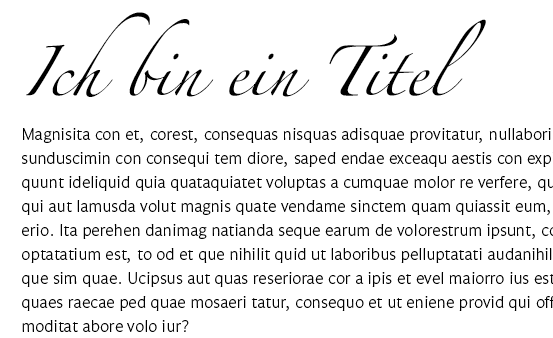
Serifenlose für Dipl-Arbeit, zur Zapfino
meine Freundin schreibt gerade ihr schriftliches Diplom in der Innenarchitektur, Thema "Flagshipstores".
Für Titel, besondere Hervorhebungen und u.U. Überschriften will sie unbedingt eine Zapfino. Und für den Fließtext eine Serifenlose. Bei beidem lässt sie nicht mit sich reden, auch Trennungsdrohungen helfen nicht. Immerhin hat sie sich von der Verdana abbringen lassen, was ich mir selbst hoch anrechne!
Nunja, und bei der Fließtextschrift schwimme ich gerade noch etwas. Hier haben eben viele Anforderungen/Eigenschaften Einfluss, ungefähr geordnet nach Wichtigkeit:
- angenehme Lesbarkeit auch bei 40+ Seiten
- passend zur Zapfino
- Überdrehtkeit/"Over-Dressed-heit" des Modebusiness
- Technische Anmutung bzw Konstruiertheit von Grundriss-Auszeichnungs-Schriften
- Verdana-Ähnlichkeit
Na, Ideen?
FF Fago? Frutiger? Univers? Museo Sans? Akzidenz-Grotesk? Neo Sans? Myriad? News Gothic? Avenir? DeLargo? Interstate (Light)?
PS: Habe persönliche Ressentiments gegen eingeschossige "a".
PPS: Gotham ist mir zu 'hip'.
Deine (OK, ihre) Kriterien klingen für mich erstmal relativ äh, schwer zu vereinen (gute Lesbarkeit, aber so technisch wie ne Grundrisszeichnung? Ich denke, da muss ne Priorisierung her. Klingt ein bisschen nach eierlegender Wollmilchsau :-) ).
For what it's worth und ganz spontan: Die angenehmst zu lesende Serifenlose, die mir auf Anhieb einfällt, ist die :biglove:Legato von Evert Bloemsma. Was da in den Balkenstärken ganz fein passiert, könnte man, wenn mans nicht besser weiß, auch für einen feinen kalligraphischen Duktus halten (tun wirklich manche Laien) – könnte also evtl einigermaßen zur Zapfino passen?
30-Sekunden-Schnelltest anbei (das ist Legato Light, 11/16).
Meine Rede, meine Rede. Dennoch könnte eure Ablehnung ja auch in konstruktiver Kritik ausarten, wie wär's? Werde ihr mal die Scriptina vorschlagen. In der Page waren in der Ausgabe vom letzten Dezember ja auch Alternativen vorgestellt, aber das passte ihr irgendwie alles nicht. :neenee: Frage diesbzgl nochmal nach.
Deswegen formuliere ich eben meine Frage allgemeiner:
Welche Serifenlose für Fließtext passt gut zu einer Schreibschrift?
Ich finde meine Frage ("Serifenlose für Diplomarbeit") hat Definitiv eine Daseins-Berechtigung, wo doch normalerweise in längeren Texten Serifenschriften zu Einsatz kommen. (Berechtigterweise, keine Frage!)
Nina's Vorschlag, die Legato, finde ich sehr ansprechend, und finde auch, dass sie im Detail etwas kalligrafisches hat! Sehr schön auch: Mediälziffern! Ob's zur Zapfino passt? Hm. Ist fies, Schreibschriften sind schon so... ganz anders.
Gerade in Sachen Mediälziffern zählen deswegen auch Scala & Fago im Moment zu den Favoriten!
Eresh, puncto Alternativen zur Zapfino schau Dir vielleicht auch die Olicana an. Isn bisschen weniger «hochkalligraphisch» und ein bisschen mehr «geschrieben»… oder dann gleich den Herrn K. :D
Ich glaube ich gehe da eh falsch ran, sollte den Gaul andersherum aufzäumen. Erst Fließtextschrift, dann Auszeichnungsschrift.
Olicana gefällt!
für den text
nichts gegen zapfino, mögen konnte ich sie persönlich noch nie und
bei dem thema finde ich sie langweilig und nicht edel.
da würde italic bodoni in versalien viel cooler. :?
oder einfach ein klassiker wie sackers heavy roman.
Ich glaube ich gehe da eh falsch ran, sollte den Gaul andersherum aufzäumen. Erst Fließtextschrift, dann Auszeichnungsschrift.
das ist zwar theoretisch richtig.
praktisch aber irrelevant, da die vorgabe nun einmal eine andere ist.
wobei sich auch bei mir "schreibschrift" (und dann auch noch zapfino) und "diplomarbeit" nicht so recht vorm geistigen auge zusammenfügen wollen, aber da musste durch.
... aber das passte ihr irgendwie alles nicht.
:neenee: Frage diesbzgl nochmal nach.
du kannst auch versuchen einem elefanten steptanz beizubringen.
:P
wenn "SIE" sich zapfino in den kopf gesetzt hat, ist diskutieren zwecklos.
da kannst du nur noch versuchen das schlimmste (verdana) zu verhindern.
Deswegen formuliere ich eben meine Frage allgemeiner:
Welche Serifenlose für Fließtext passt gut zu einer Schreibschrift?
öh ... :party: optima?
nagut. vorschlag zur güte: gloriola.
Nina's Vorschlag, die Legato, finde ich sehr ansprechend, und finde auch, dass sie im Detail etwas kalligrafisches hat!
für meinen geschmack ist die zu kräftig und hat eine zu grosse x-höhe, um gut zur zapfino zu passen. da finde ich die itc legacy sans besser.
(Und die Legato ist auf jeden Fall so ein Kandidat – da ist mir persönlich die Regular, je nach Anwendung, schon fast zu fett.)
Habt ihr noch Ideen für eine Kalligrafieschrift mit ausgeprägten Ober- & Unterlängen, aber nicht zu ornamental?
Mitgeliefert bei der CS3 (soweit ich mich erinnern kann) ist auch die Bickham Script, die bei Bedarf auch massenweise Alternativglyphen und Ligaturen hat.